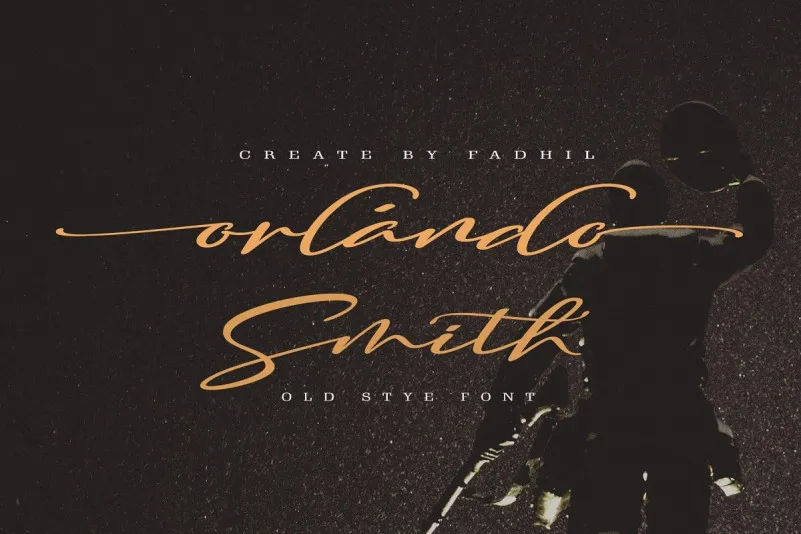
Descubra Orlando Smith Script Font, uma elegante e vibrante tipografia script criada para tornar sua arte visual ainda mais incrível. Este tipo de letra é perfeito para aqueles que buscam algo sofisticado com um toque de energia, ideal para uso em logotipos femininos, embalagens de produtos, cartazes, roupas personalizadas, selos e até mesmo convites de casamento. M.0Type lançou Orlando Smith Script Font trazendo mais de 236 ligaturas estilizadas, garantindo uma variedade infinita de possibilidades para seus projetos. Seja você um designer de logotipos, gráfico ou até mesmo um artesão da moda, Orlando Smith Script tem tudo o que precisa para aprimorar seu trabalho. Com seu design distintivo e moderno, Orlando Smith Script é perfeito para diversos usos, incluindo cartazes, escrita ao vivo, logotipos, postais, t-shirts, selos e até mesmo convites de casamento. Sua natureza vibrante e sofisticada o torna um verdadeiro favorito entre os designers que procuram uma fonte que seja tanto original quanto versátil. Descubra por si mesmo como Orlando Smith Script pode transformar seu trabalho gráfico em algo único e incrivelmente belo. Ele está esperando para ser adicionado ao seu arsenal de ferramentas digitais, fazendo você destacar na multidão dos designers e criadores que desejam tornar seus projetos ainda mais memoráveis.